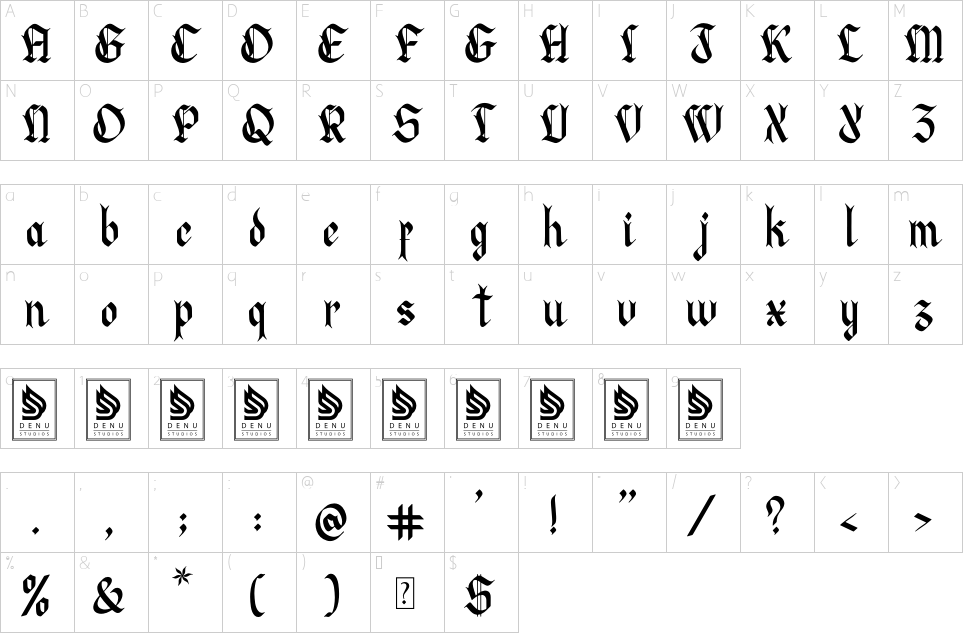
Descubra a beleza da Manthra Klaussa font em sua próxima projetada gráfica. Desenvolvida pela Denustudios, essa elegante fonte de 1001 Free Fonts é um recurso valioso para profissionais e aficionados no design. Através dela, você pode adicionar um toque único e sofisticado a qualquer projeto, seja ele para o site, o livro, ou até mesmo a camiseta. Com seu design cuidadosamente concebido, a Manthra Klaussa oferece uma variedade de opções para complementar o seu trabalho. Sua download gratuita facilita a inclusão dessa fonte na sua paleta, tornando-o um acessório indispensável em qualquer projeto visual. Desde o seu download pela primeira vez, a fonte já foi utilizada 376 vezes, indicando a sua crescente popularidade. Engane-se se pensar que é apenas uma fonte, a Manthra Klaussa é um componente vital para criar experiências visuais que destacam o seu trabalho.